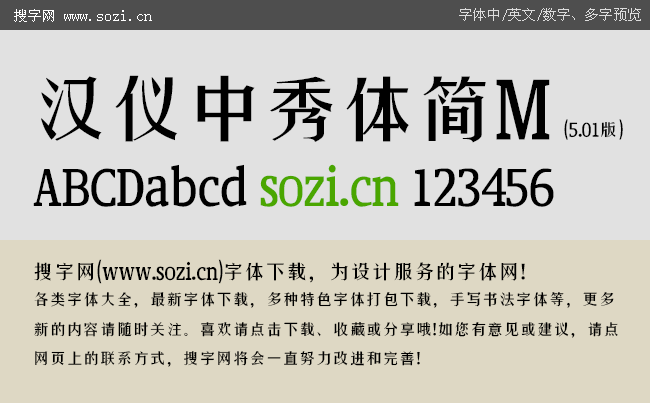
漢儀中秀體簡M
搜字網給大家提供一款漢儀中秀體簡體中文字體下載。漢儀中秀體字形結構穩定,配合設計簡潔的筆畫,排版時整體線性效果更加突出,使閱讀更加流暢。 筆畫風格上融合了黑體與宋體的特征,線條簡潔,氣質圓柔、秀美,風格靈動、時尚。筆畫間的相互呼應更使得字體整體結構統一完整、避免了結構的呆板、生硬?蓱糜谄矫嬖O計、出版印刷、廣告設計、包裝設計等領域。